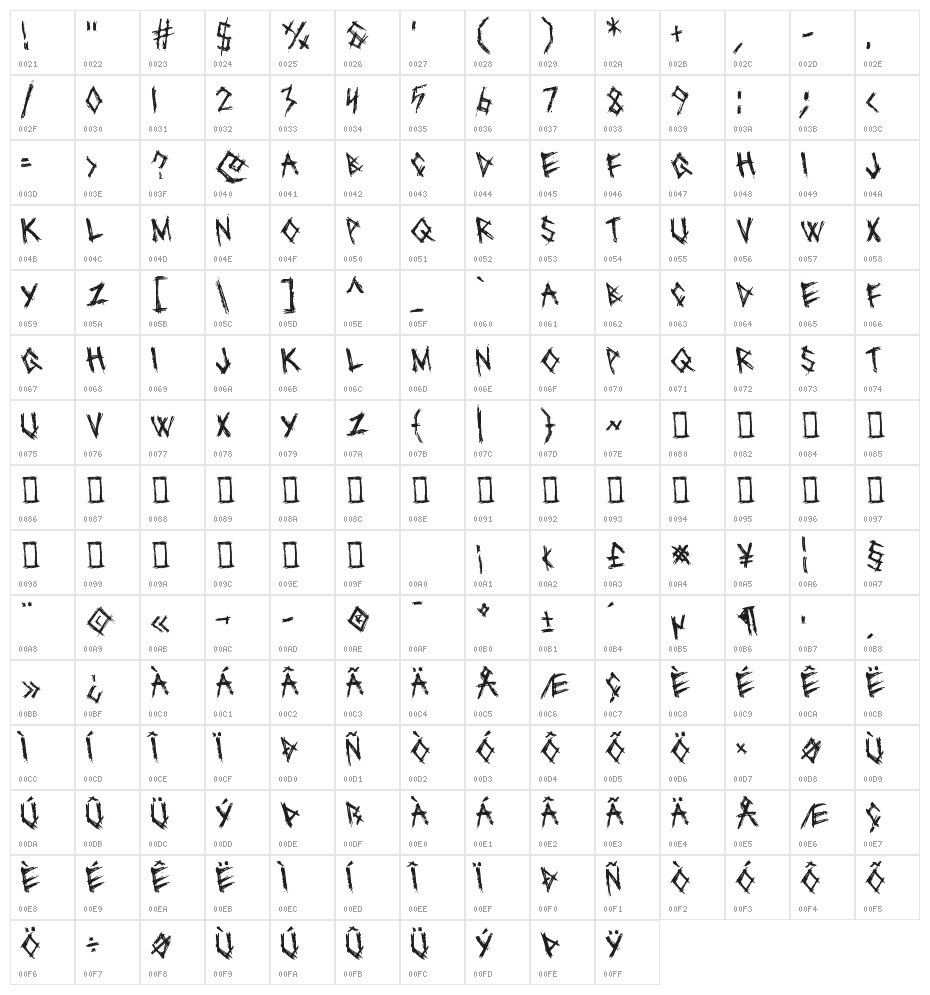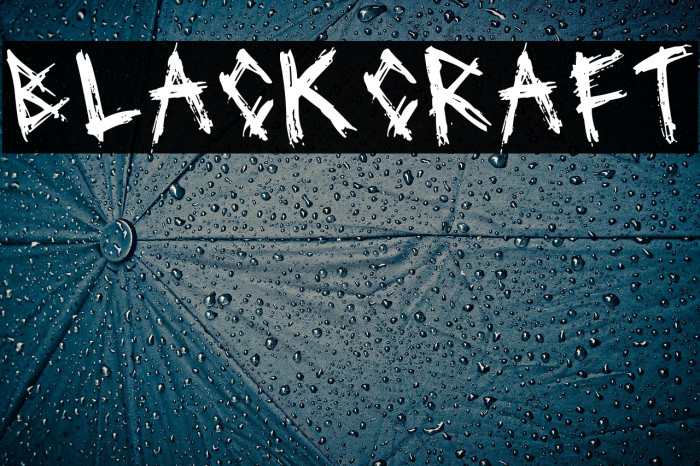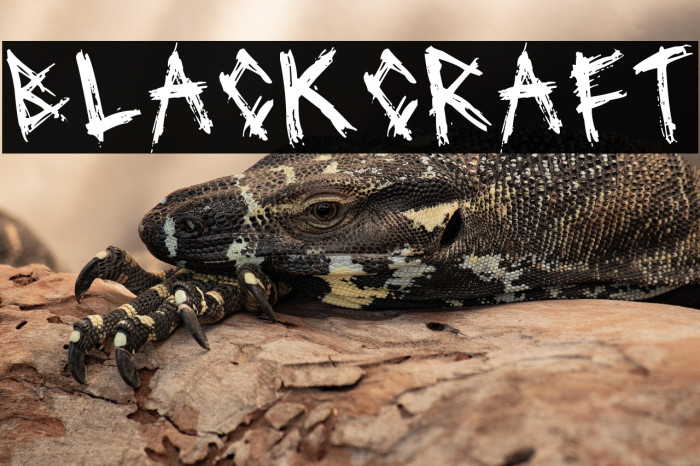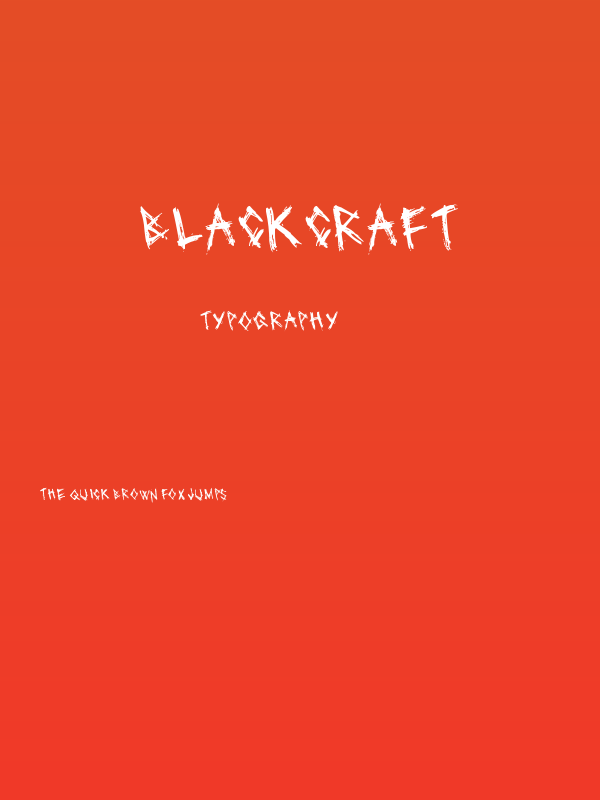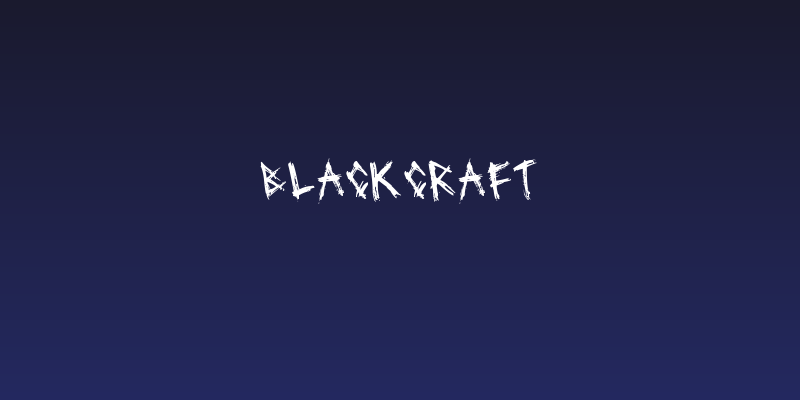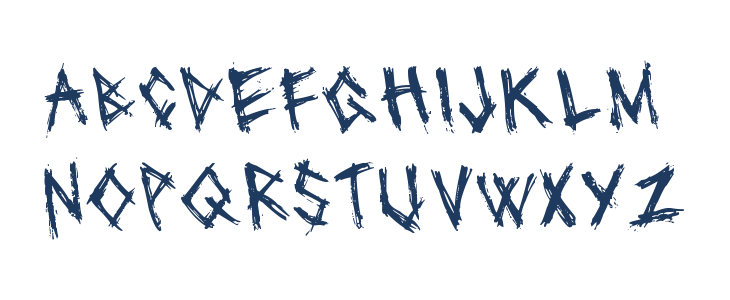
Blackcraft Font
✎ Messy
| Stile generale | Edgy, Rebellious, Raw |
| Progetti proposti | Perfect for album covers, posters, horror-themed designs, and alternative fashion branding. |